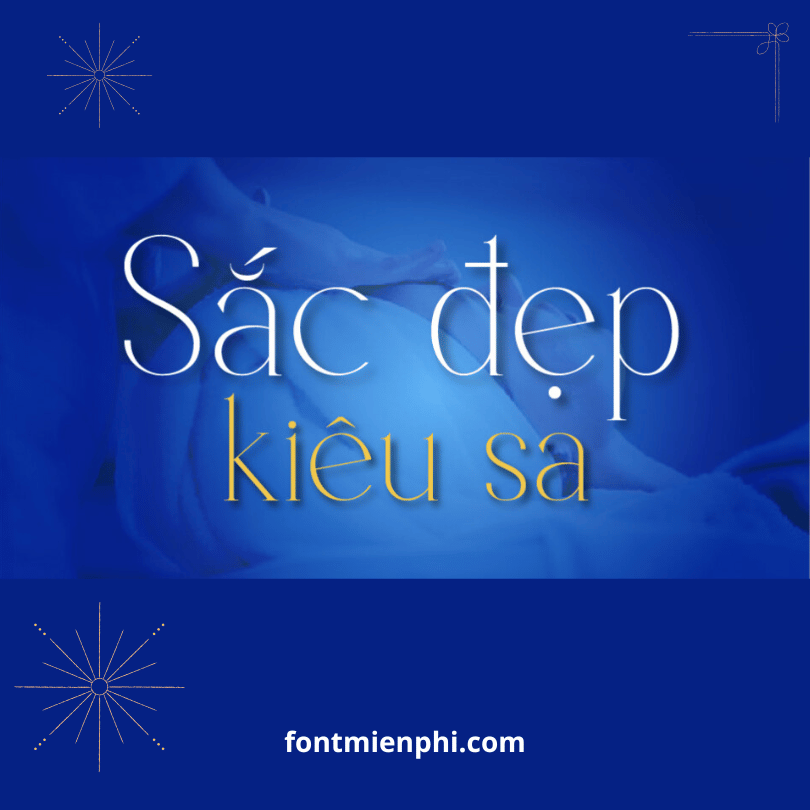
Font Việt hóa 1FTV VIP Borcha
Font Việt Hóa 1FTV VIP Borcha – Phong Cách Mạnh Mẽ & Đột Phá
Là một trong những siêu phẩm độc quyền từ 1FirstFont1FTV VIP Borcha được thiết kế dành riêng cho các dự án cần sự mạnh mẽ, cá tính và đột phá trong từng nét chữ.
ĐẶC ĐIỂM NỔI BẬT:
✔ Việt hóa hoàn hảo: Hỗ trợ đầy đủ bộ ký tự tiếng Việt, chuẩn Unicode
✔ Phong cách độc đáo: Nét chữ đậm, góc cạnh nhưng vẫn giữ được sự tinh tế
ỨNG DỤNG VƯỢT TRỘI:
• Thiết kế logo doanh nghiệp
• Banner quảng cáo ấn tượng
• Ấn phẩm truyền thông sốc
• Thiết kế bao bì sản phẩm
• Nội dung digital marketing
1FTV VIP Borcha – Sự lựa chọn hoàn hảo cho những ai muốn tạo dấu ấn khác biệt!